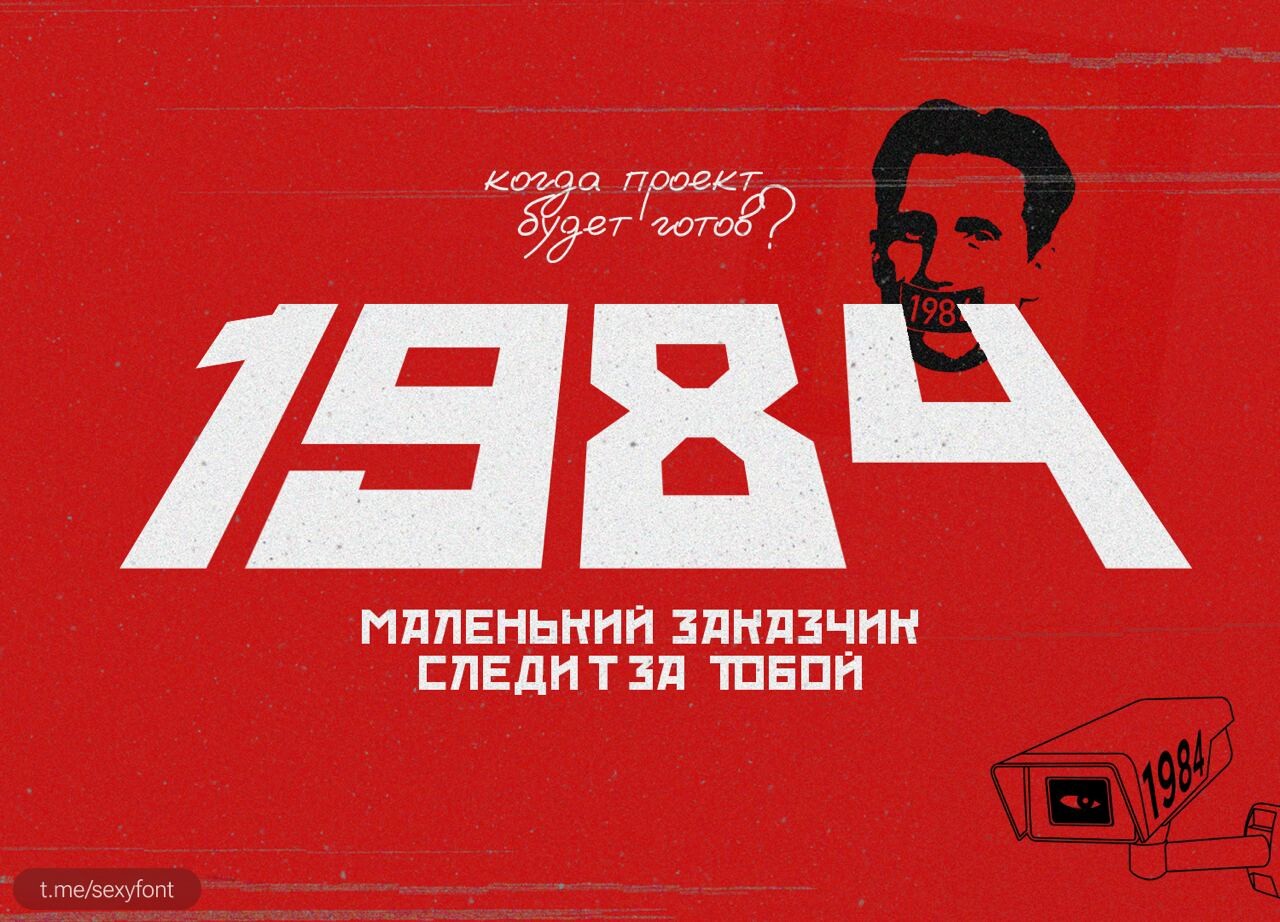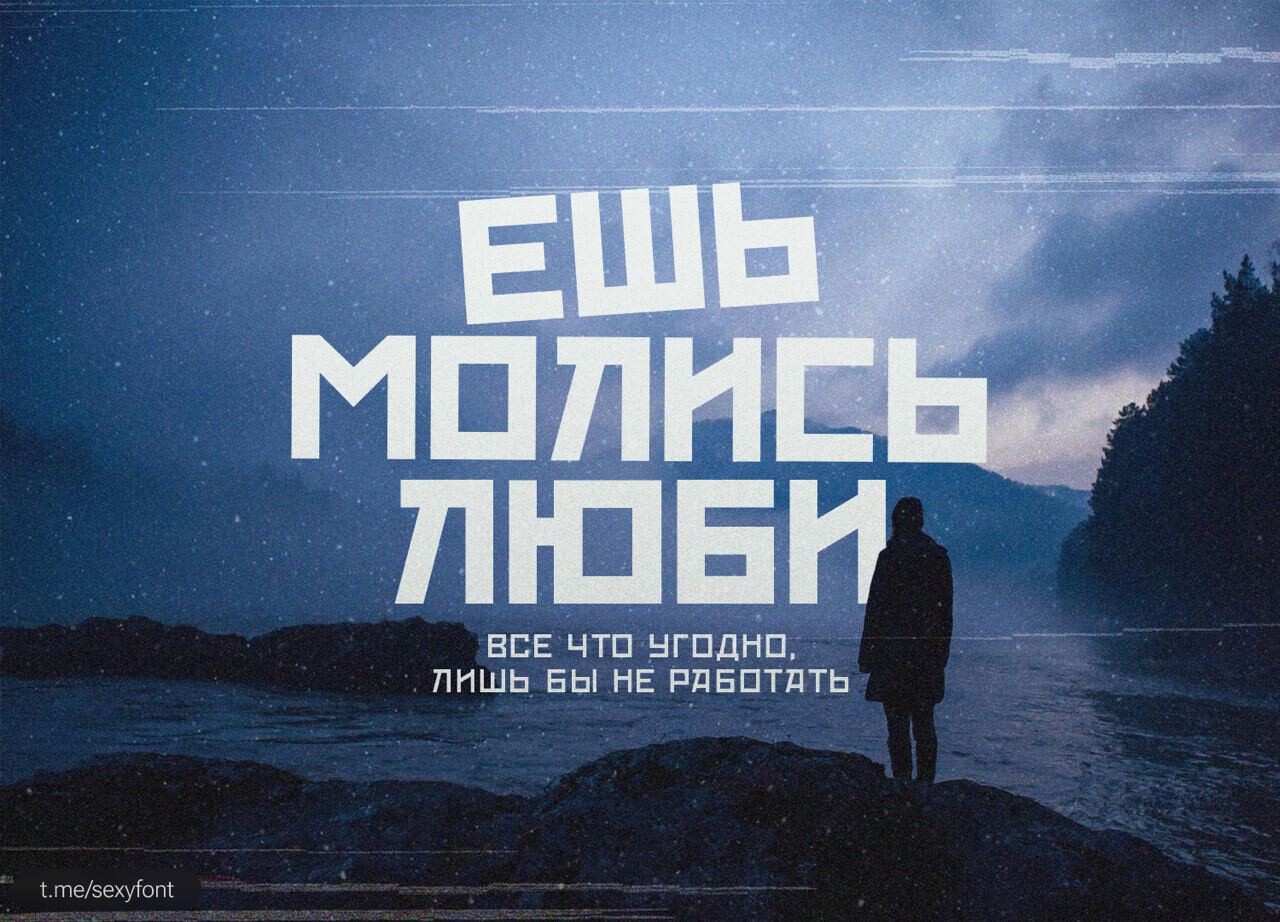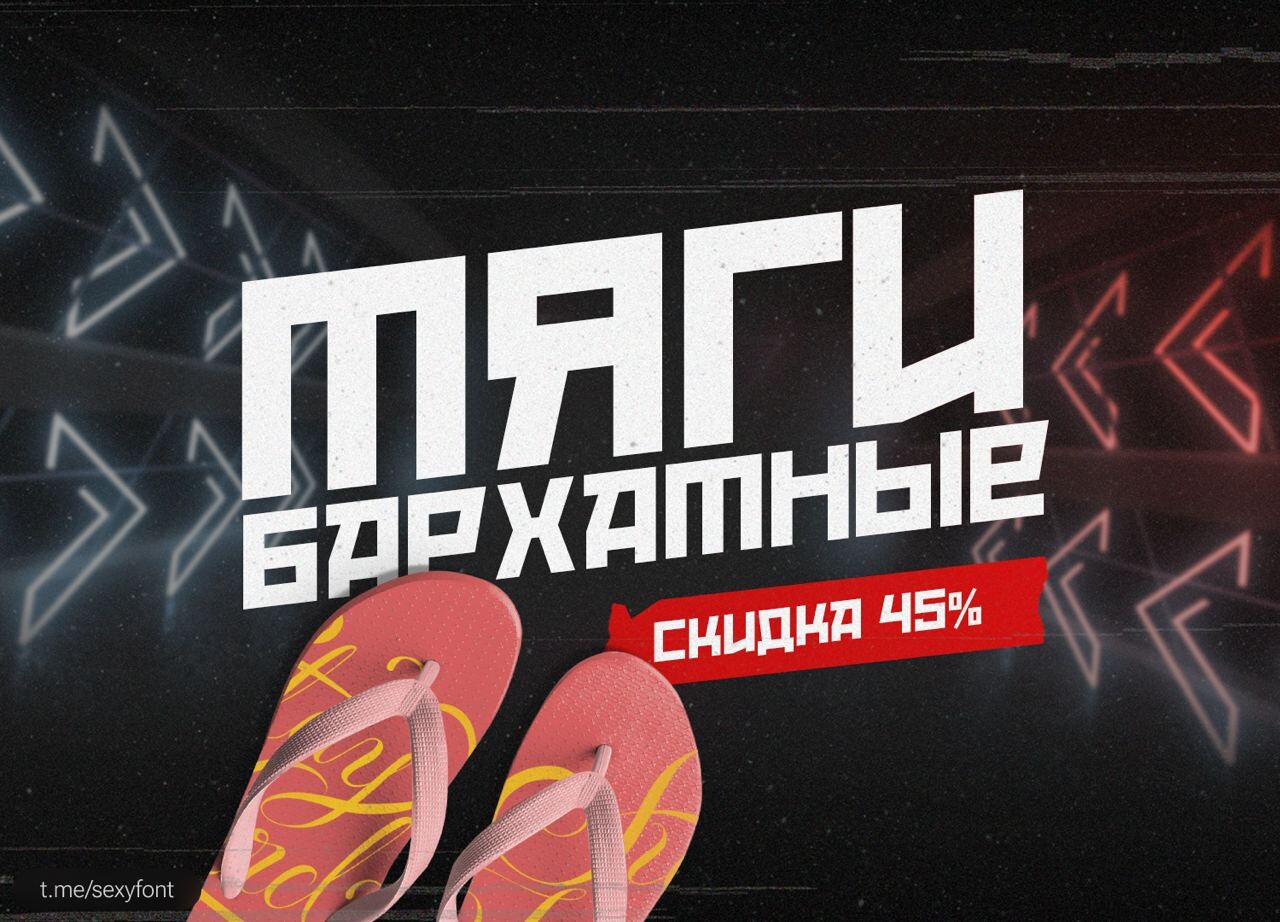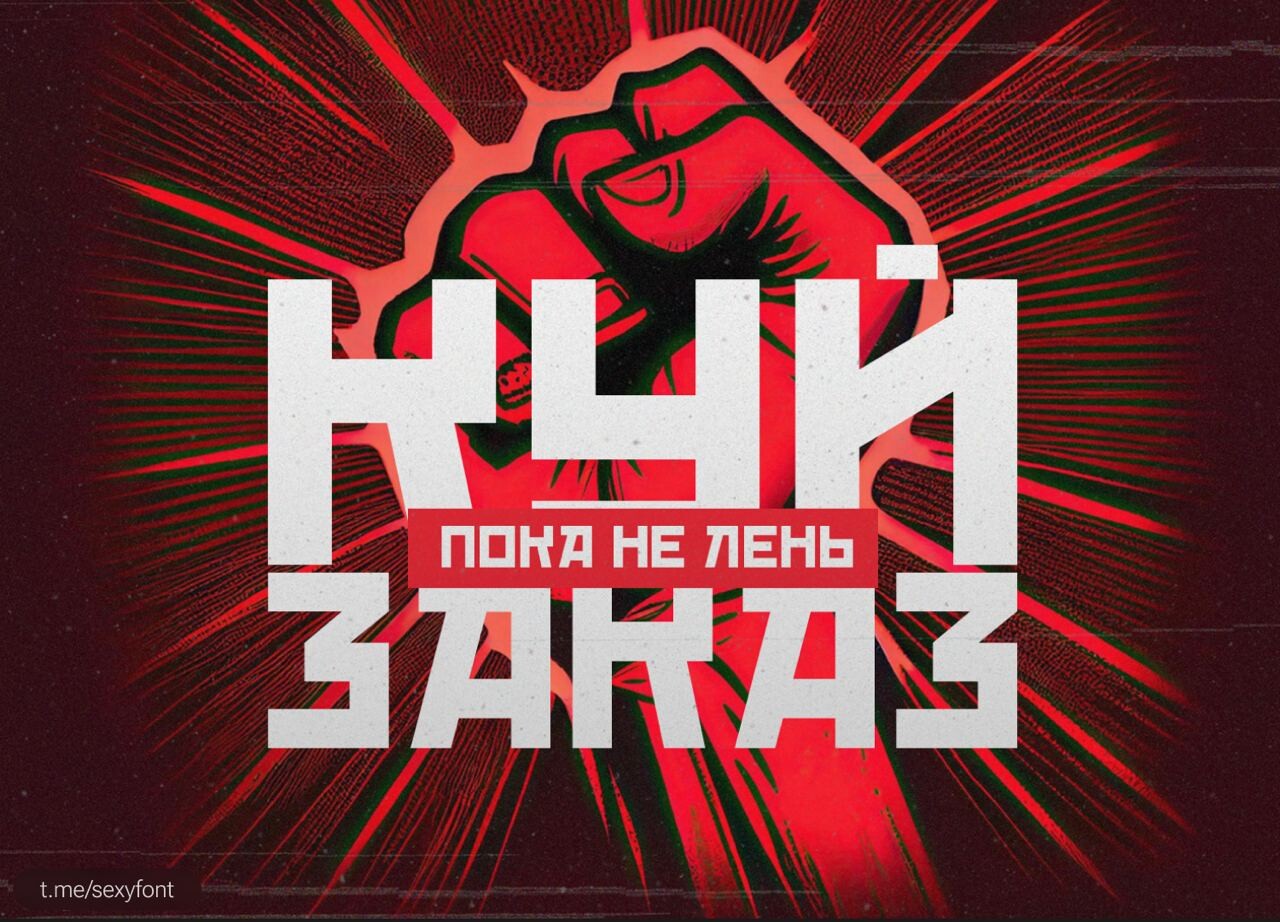
Шрифт в стиле конструктивизма, вдохновленный российскими агитационными плакатами, завоевал популярность, особенно в американских фильмах вроде R.E.D, Die Hard 5 и Repo — The Genetic Opera. Его также можно увидеть на обложке сингла Рианны "Русская рулетка".